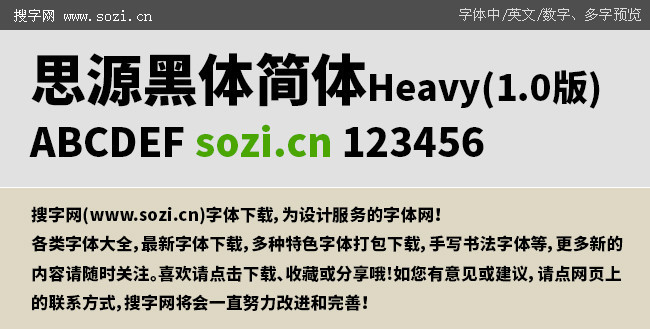
思源黑體簡體Heavy1.0
搜字網(wǎng)提供一款思源黑體簡體Heavy1.0中文字體下載,思源黑體是一款由谷歌聯(lián)合Adobe發(fā)布全新開源字體,是一款免費、開源黑體字體?晒餐尸F(xiàn)一致的視覺美感。本作品適用于書籍排版、報紙排版、畫冊設計,網(wǎng)頁設計等應用。